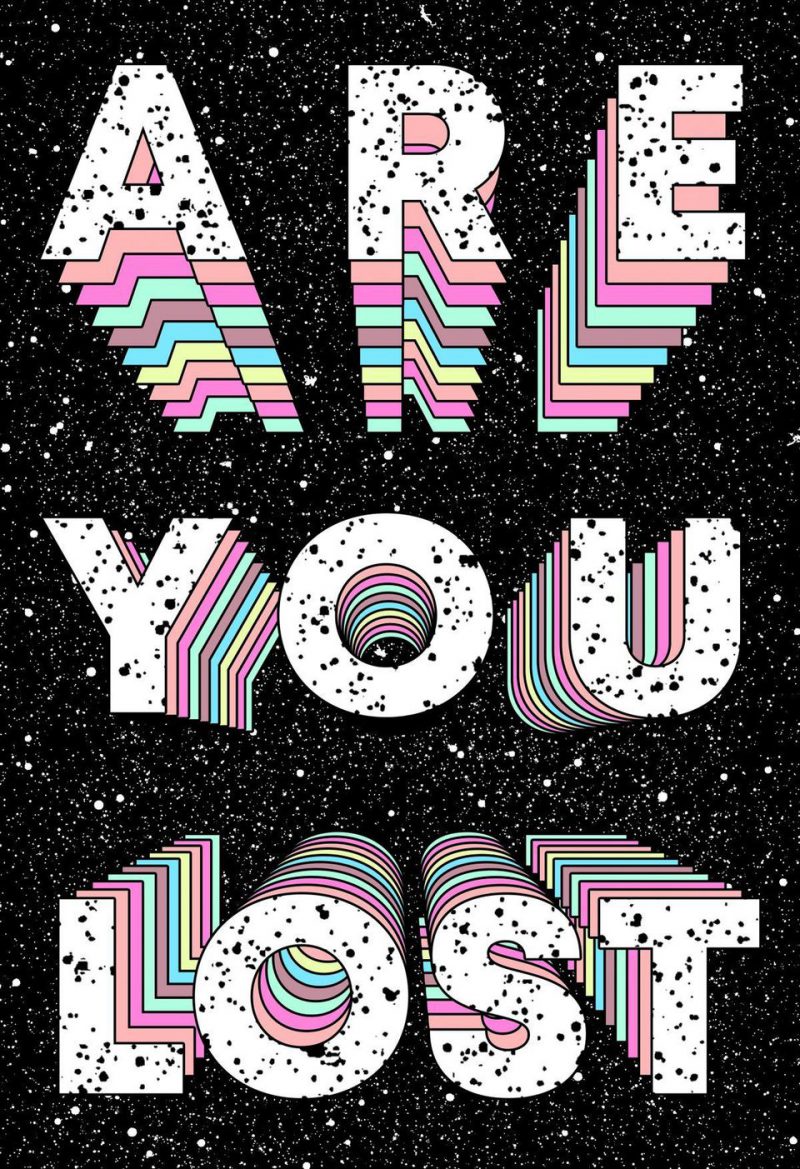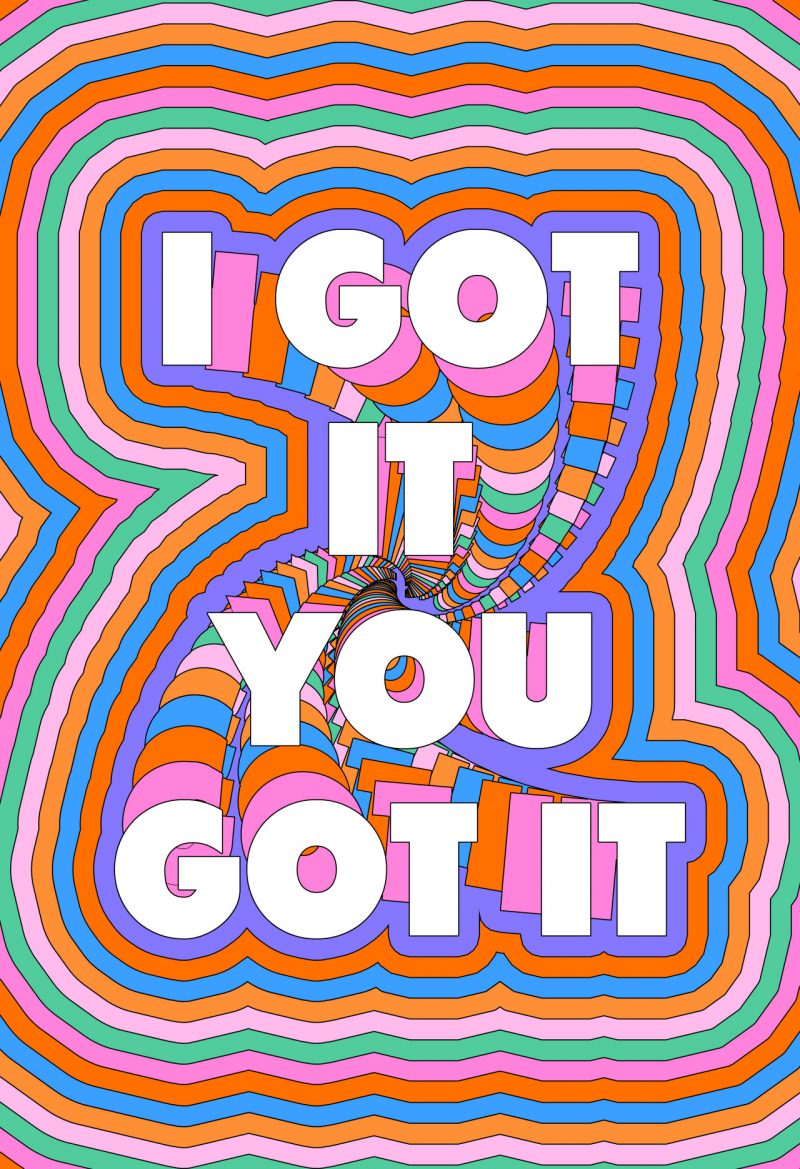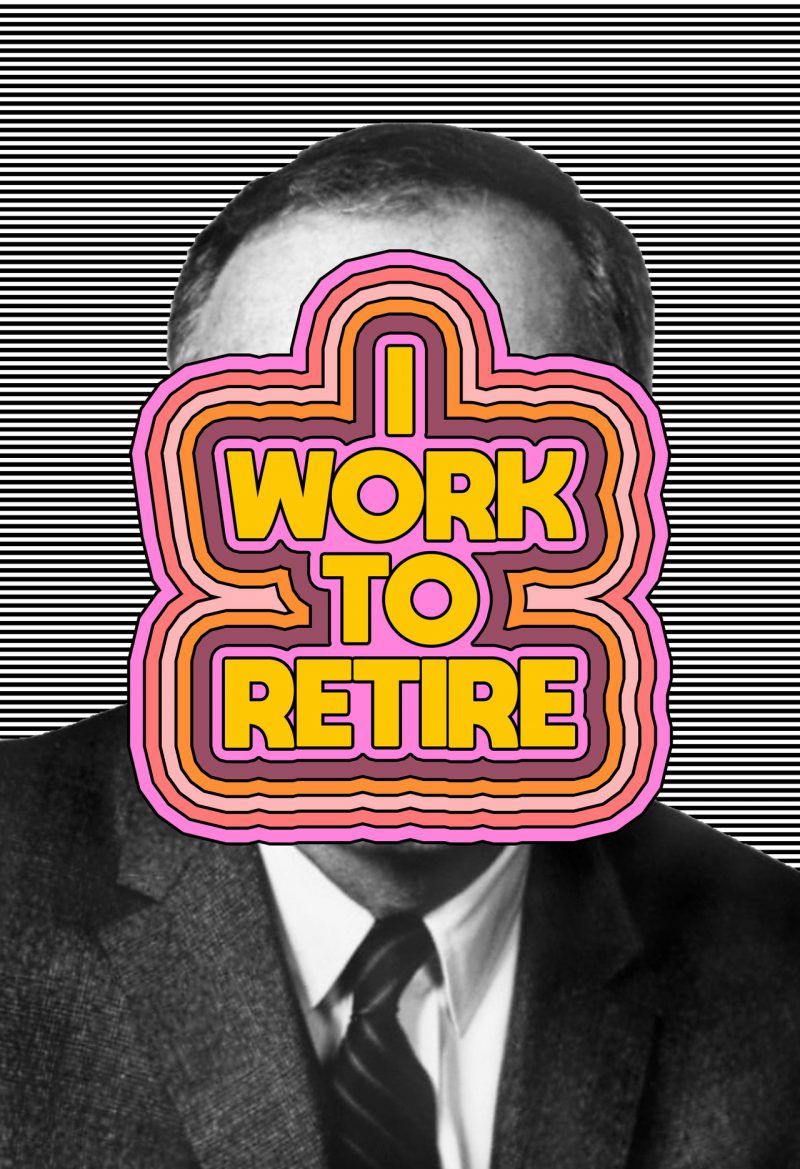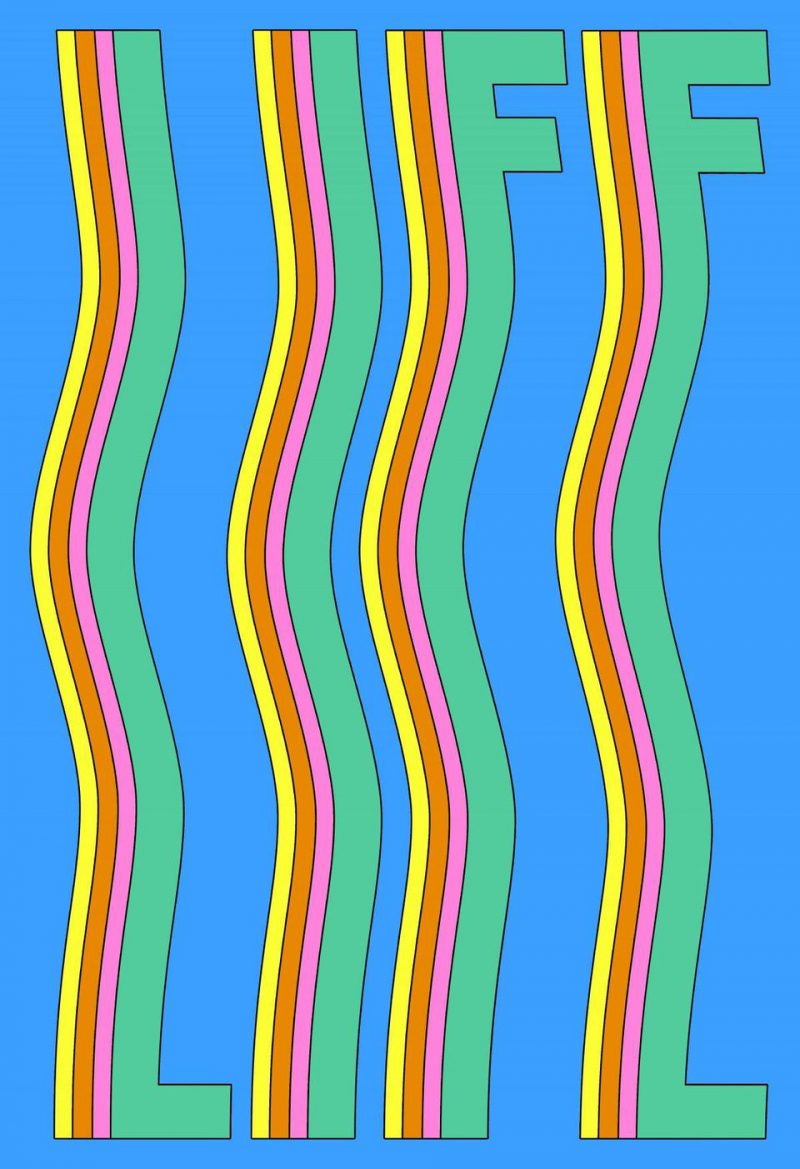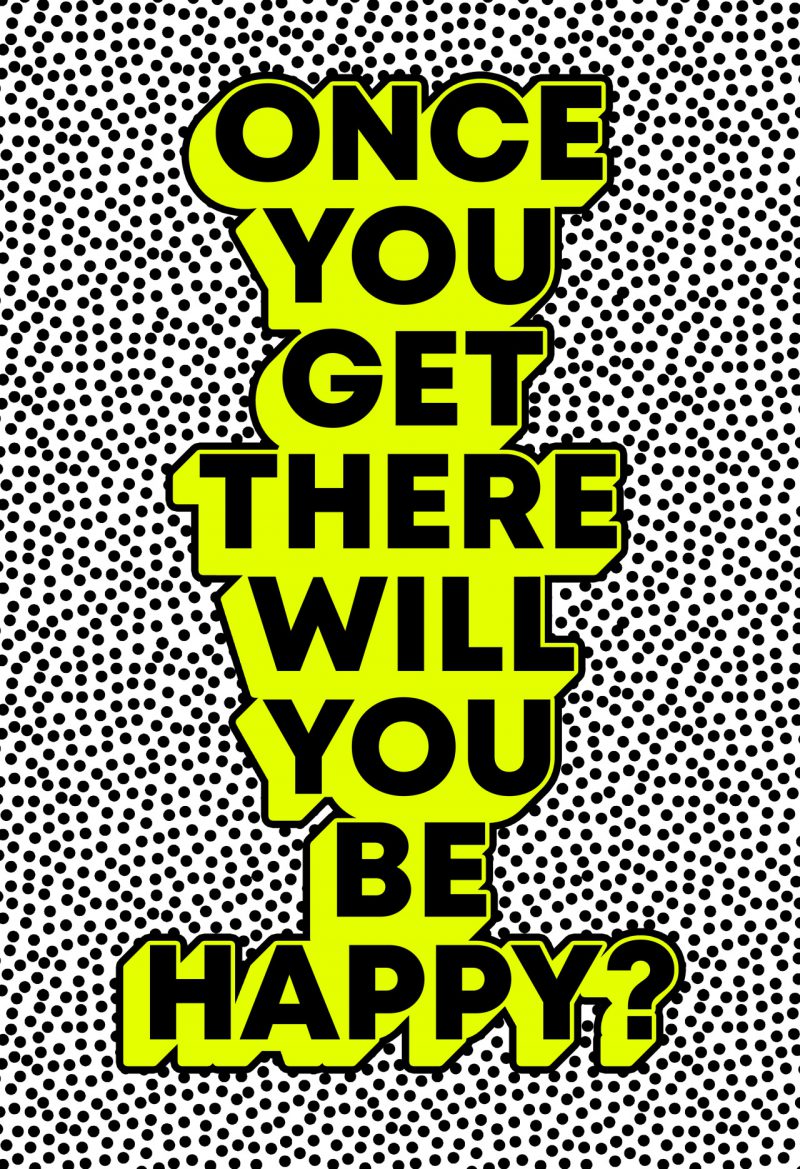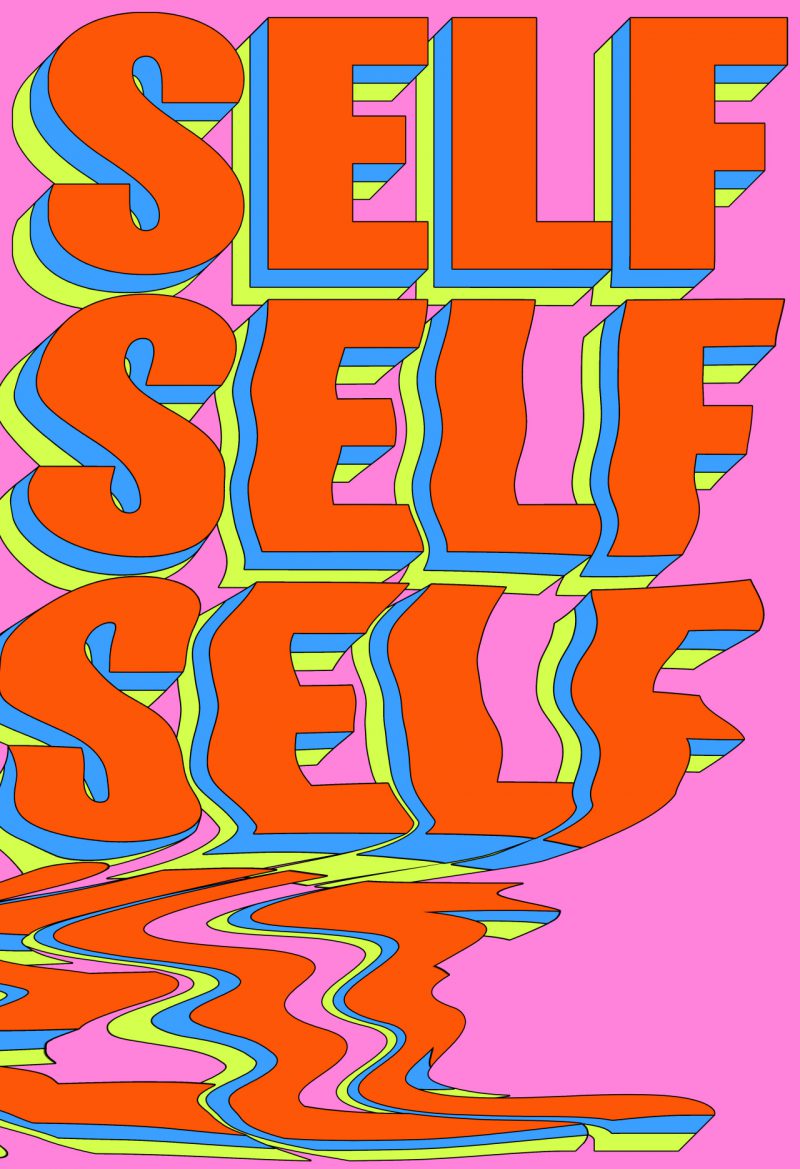
El collage psicodélico de Tyler Spangler. Diseño, tipografía, arte y psicología
Un «histórico» de la era postdigital
¿Quién es Tyler Spangler? Si tienes una cuenta de Instagram seguro, en algún momento, has visto al menos uno de sus trabajos. Incorrectas, difíciles de digerir, (re)cargadas de color y mensajes subliminales, sus piezas contribuyeron en gran medida con el resurgimiento y la buena salud de collage digital, tan de moda hoy en día.
Nacido y criado en California, en una familia con una fuerte inclinación artística, su formación académica se repartió en partes iguales entre Psicología y Diseño Gráfico. Con apenas 34 años, este «histórico» de la era postdigital, con más de 2.000 piezas en su haber, ha conseguido que gigantes como Adobe, Chanel, Nike, Red Bull o Samsung confiaran en su criterio para transmitir sus respectivos mensajes.
Aunque su obra sigue pivotando sobre el collage, una de sus vertientes más tipográficas está llamando mucho la atención. Palabras, frases, solas o repetidas con mayor o menor sentido; tipos estirados, distorsionados, gigantes o diminutos, esta nueva propuesta de Tyler Spangler, aunque reconoce que está recién en etapa de experimentación, es toda una bocanada de aire fresco.